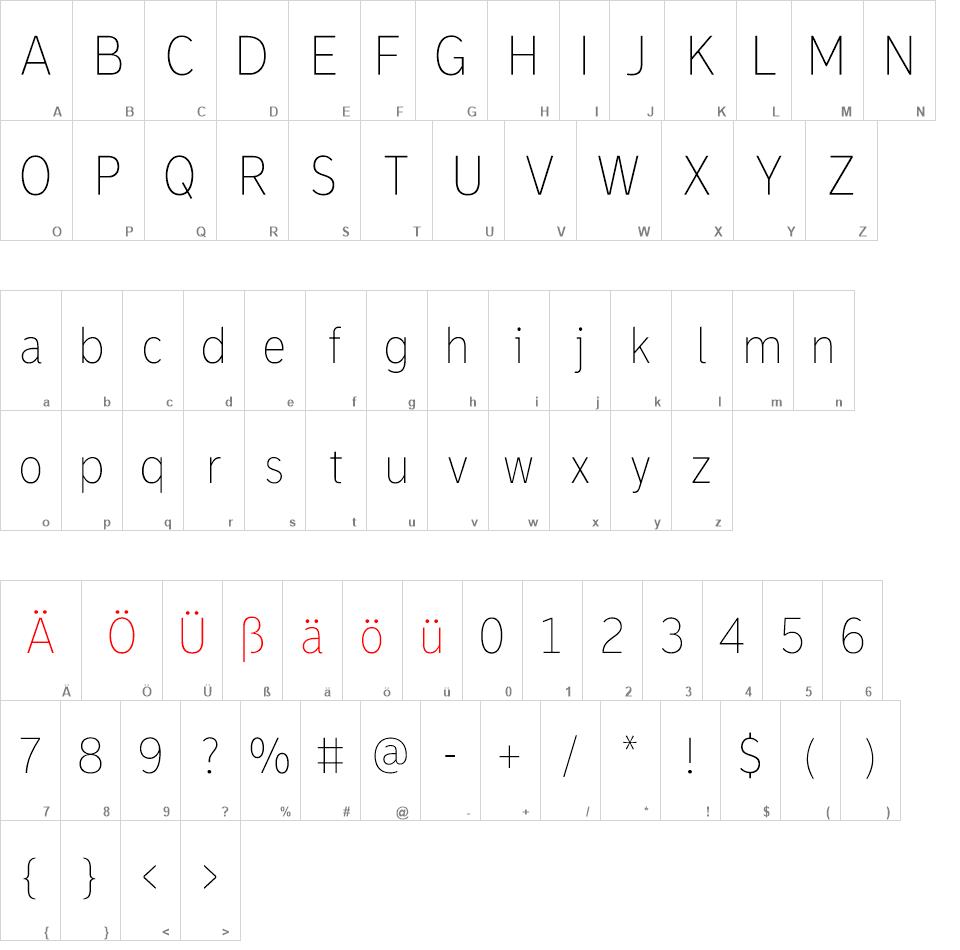
Madras
Madras font
Design und Produktion begannen mit Thomas Andromedas Charakter und verbreiteten sich über zwei Jahre, inspiriert von der Straßen- und Straßenbeschilderung. Die Schrift ist platzsparend, lesbar und letztlich elegant. Madras bietet die Einfachheit der Schreibformen, wie zum Beispiel Helvetica, und wird mit den modernen beschreibenden Merkmalen von Interstate-ähnlichen Schriften kombiniert, um eine hybride Schriftart zu schaffen, die auf jede Situation angewendet werden kann.
Der Name Madras wurde aus einem Wettbewerb ausgewählt, den wir auf Twitter betrieben haben. Madras ist die Straße in der TDF-Zentrale, die direkt mit der Inspiration des Charakters verbunden ist.